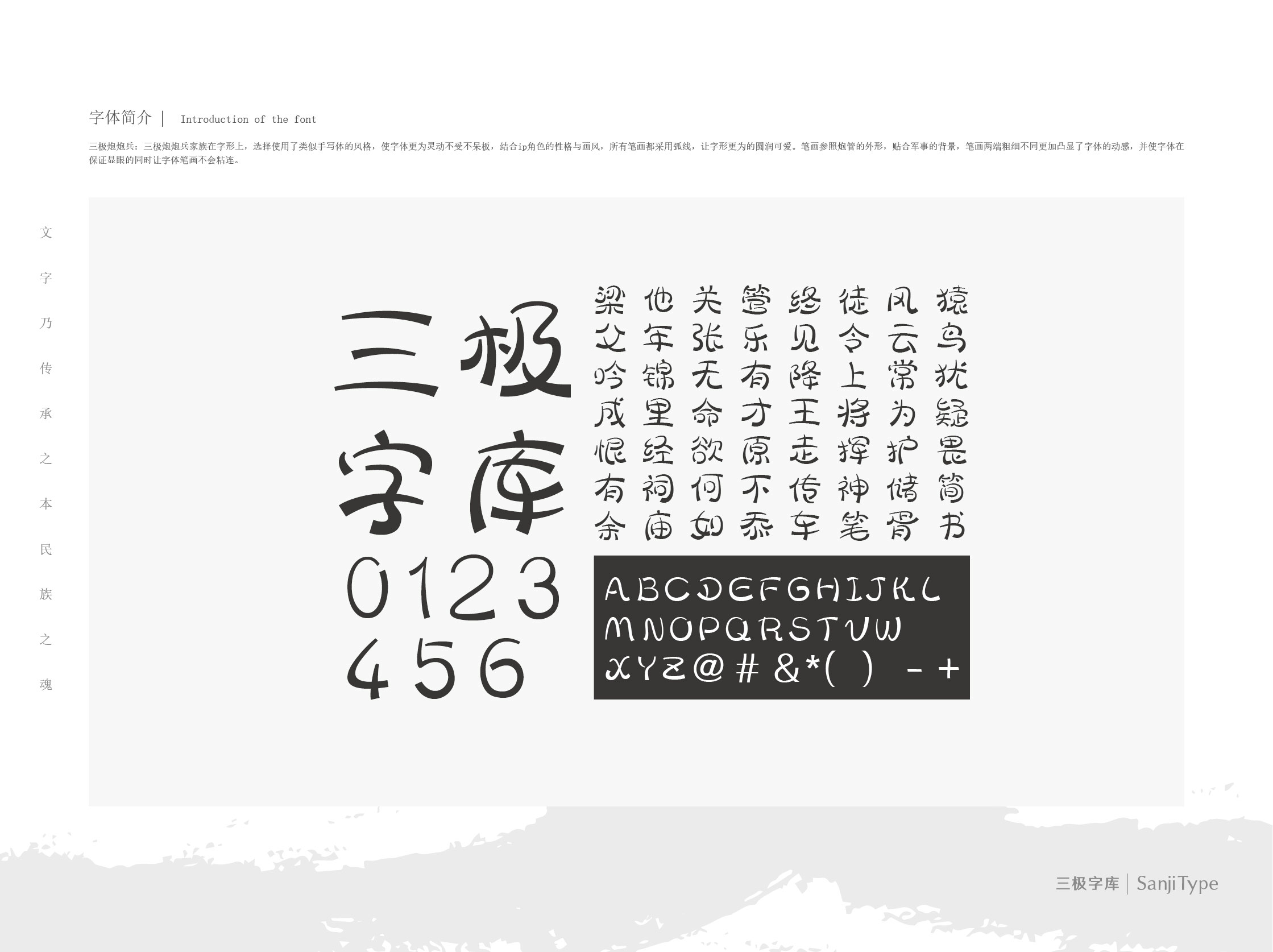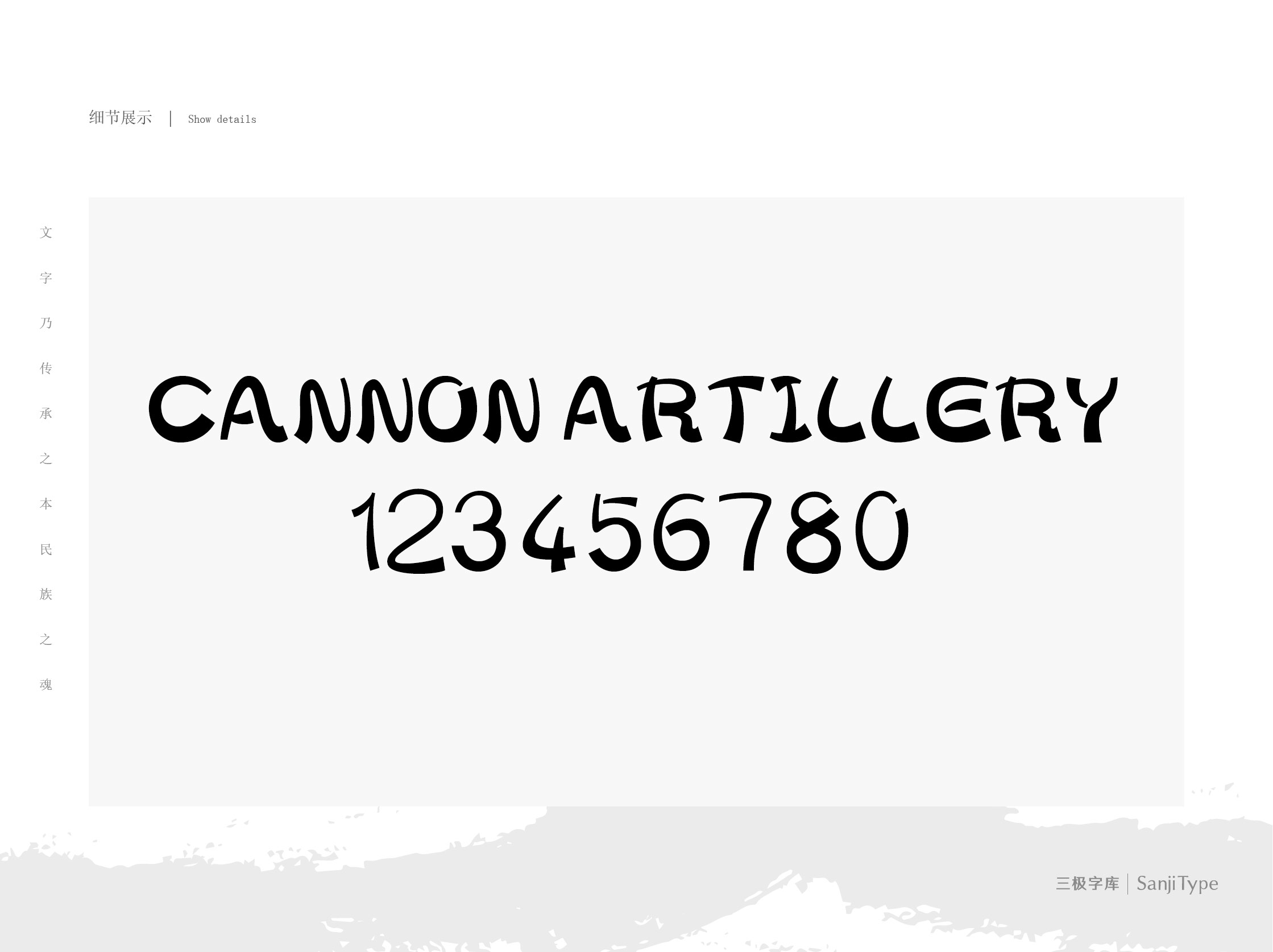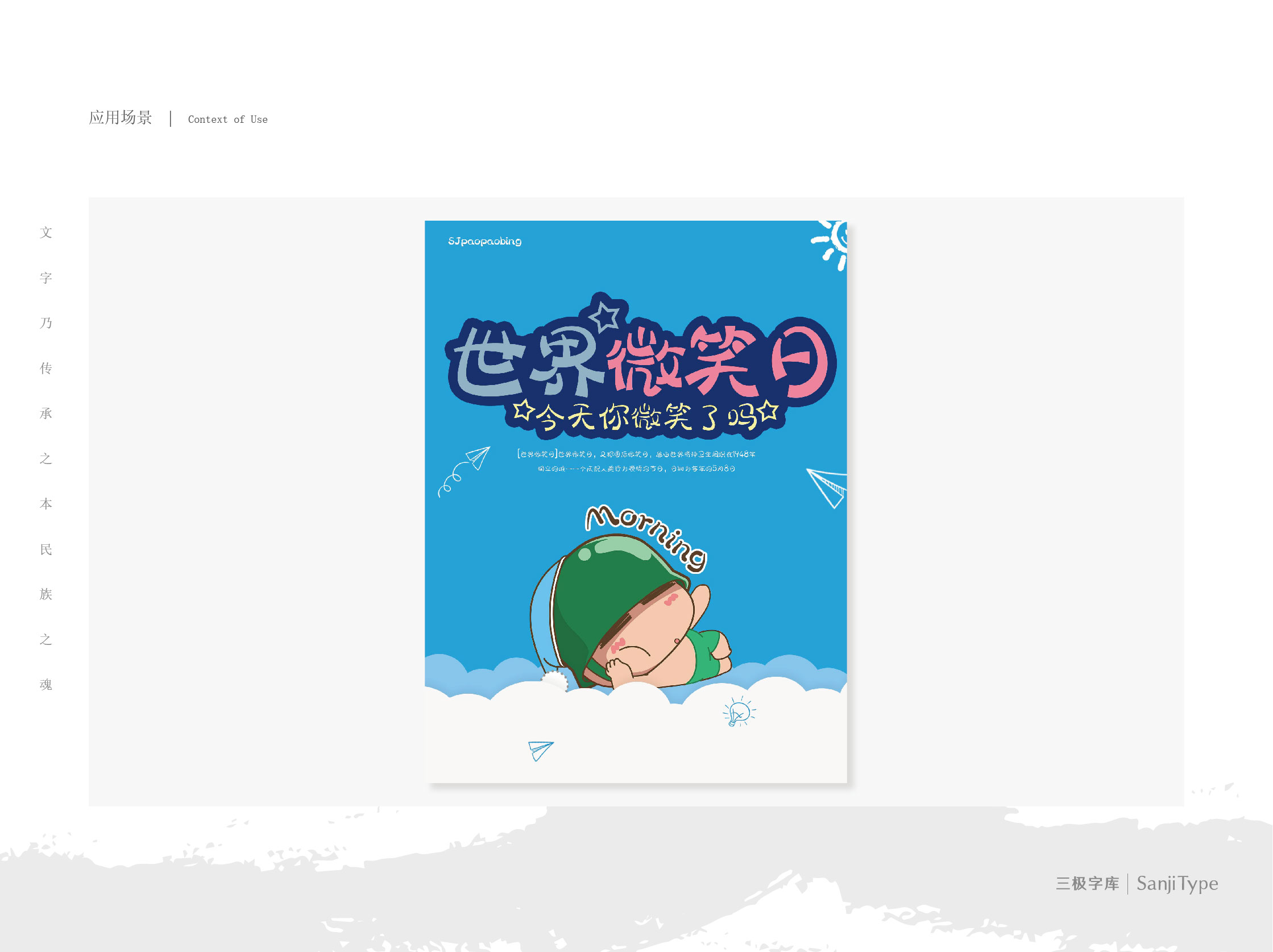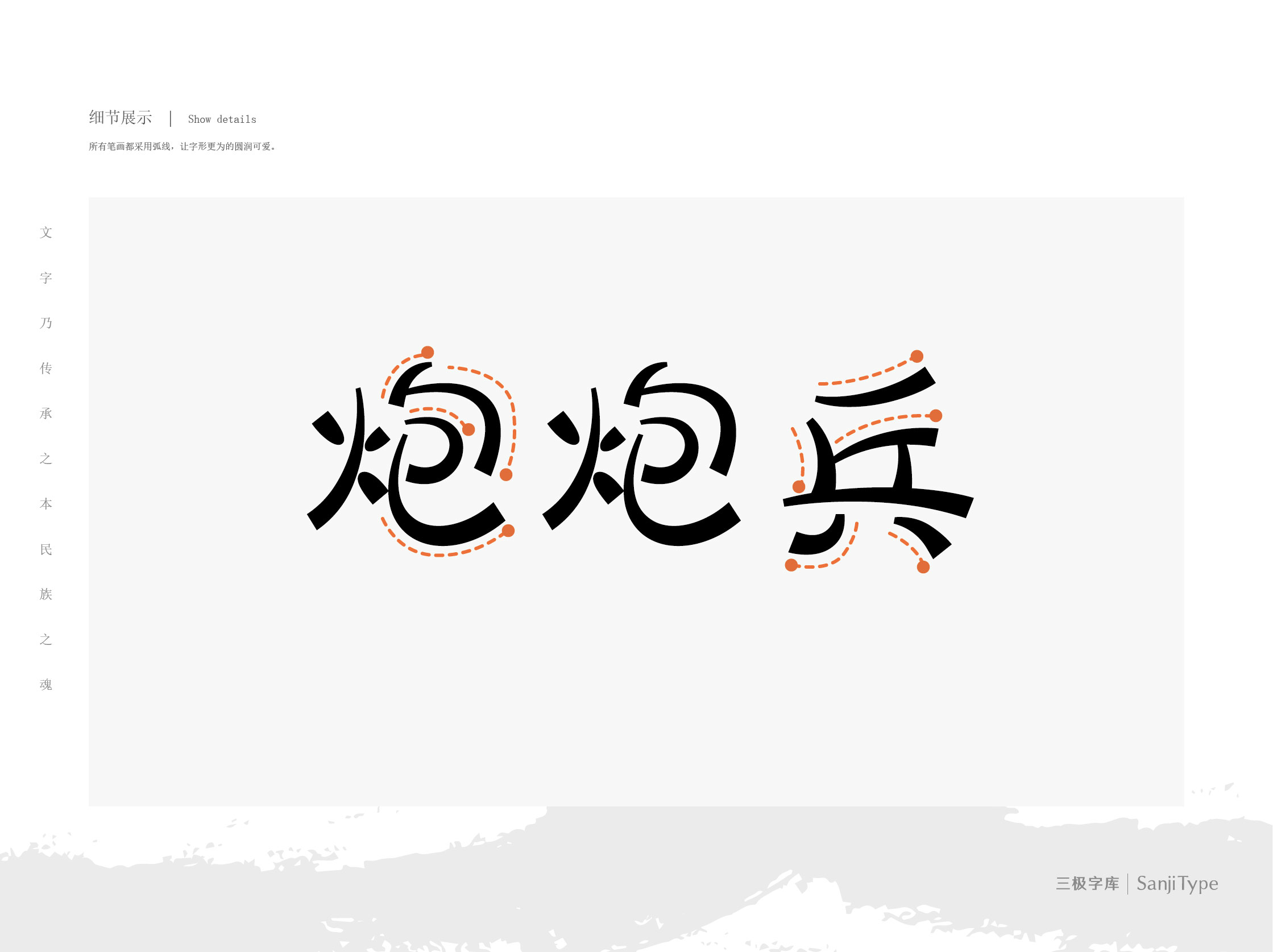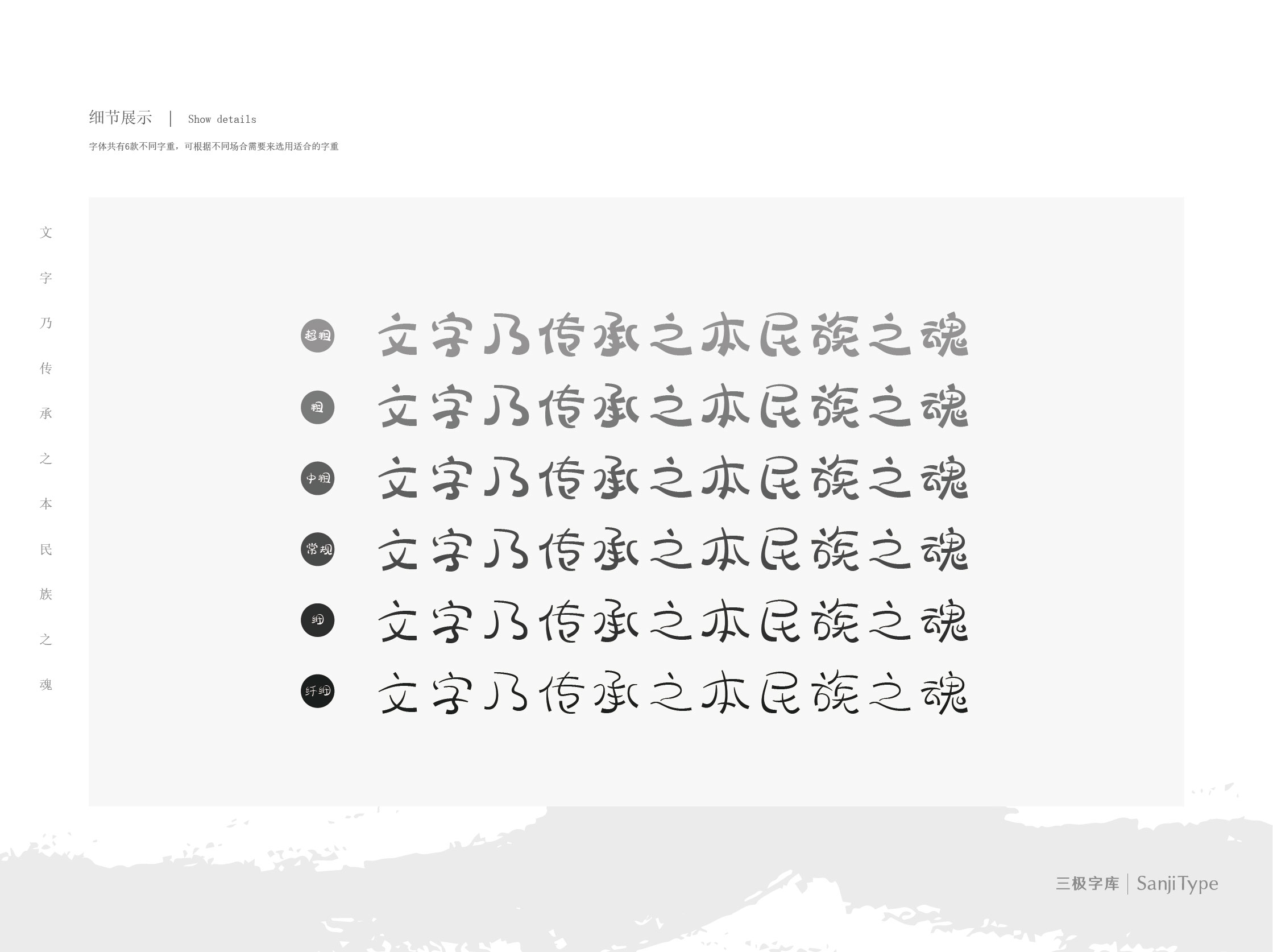
三极炮炮兵家族
三极炮炮兵 细
三极炮炮兵
三极炮炮兵 中粗
三极炮炮兵 粗
三极炮炮兵 超粗
三极炮炮兵 纤细
三极炮炮兵:借手写体风格表现出炮炮兵这一ip鬼马俏皮的屏幕形象。字形上,字体结构灵动不呆板,笔画造型上,所有笔画都采用弧线,整体圆润可爱。
同时,还参照炮管的外形,笔画两端粗细不同更加凸显了字体的动感,并使字体在保证显眼的同时让字体笔画不会粘连。